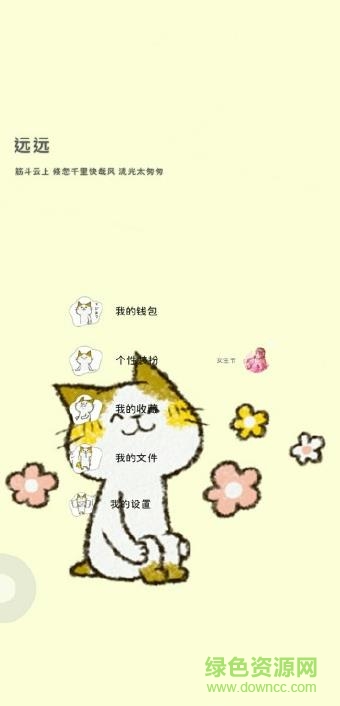
字體兜兜體
兜兜體ttf微博慧心的十分不錯的字體樣式,能夠在電腦上以及大家的手機上進行使用,讓你能夠感受到十分獨特的字體樣式風格,能夠進行系統(tǒng)字體設置以及聊天字體設置,快來綠色資源網下載吧!
慧心兜兜體小編點評
兜兜體字體在其寫作以及閱讀的過程中都能夠帶給你不錯的視覺體驗,同時也能夠運用到你生活中所需要的各類媒體制作過程中獲得最佳視覺體驗!
慧心兜兜體
字體兜兜體ttf字體介紹
1.字體能夠在眾多平臺上使用,旨在提供用戶們顯示視覺體驗
2.字體的發(fā)展十分悠久,還有眾多的最新字體在不斷的制作而來